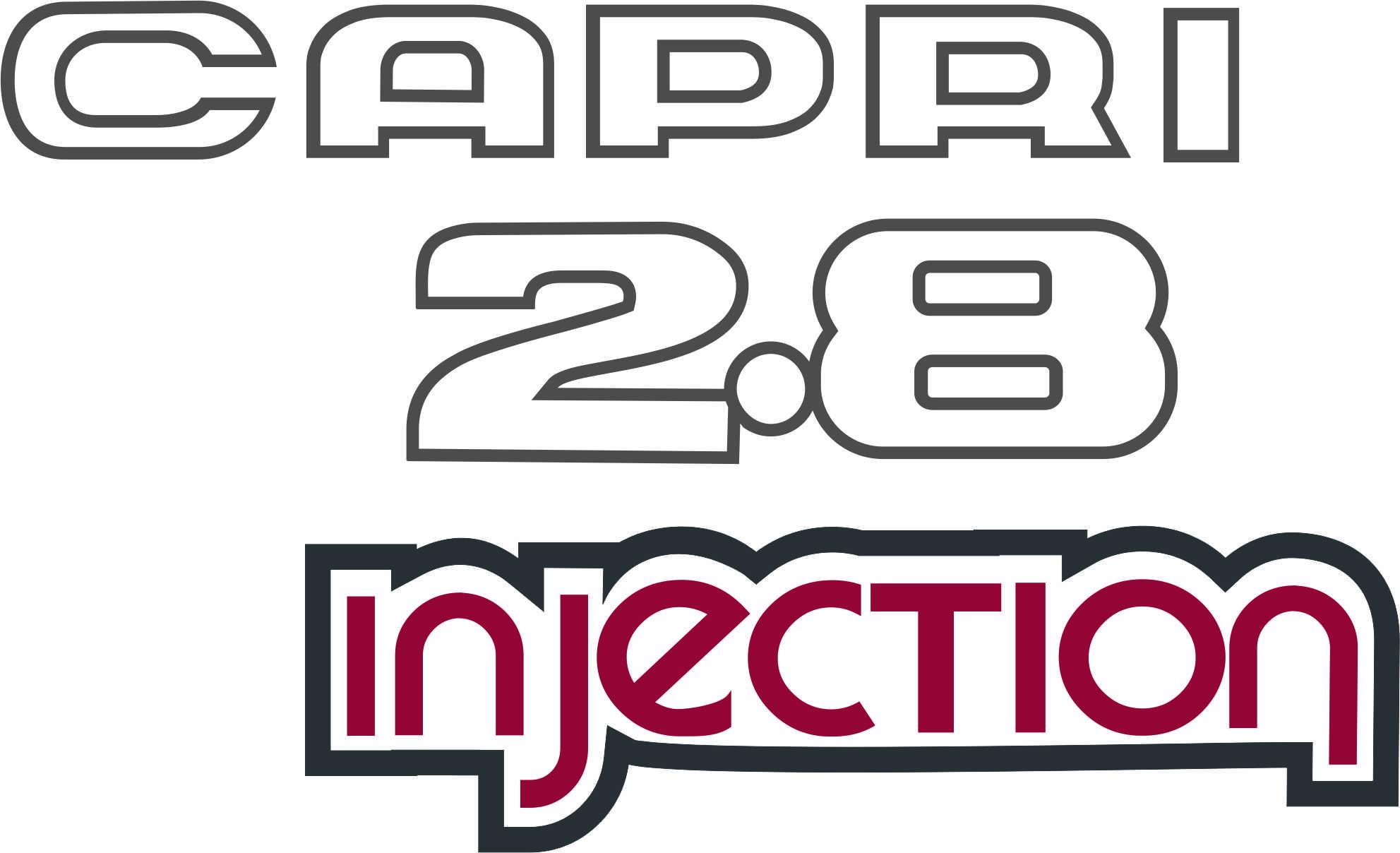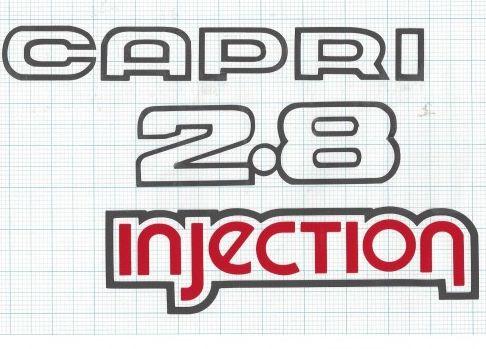
Suche die schrift von Capri 2.8
Da ich Leie bin und nichts finde, kann mir velleicht jemand hier helfen
Welche Schrift ist das von folgendem Bild ..
Solche Schriftzüge wurden üblicherweise gezeichnet, gestaltet, konstruiert oder wie auch immer, aber nicht aus einer bestehenden Satzschrift erstellt. Ich würde in diversen Ford-Foren schauen, ob das jemand schon nachgebaut und vektorisiert vorliegen hat.
Viel mehr als damit wird man dir wohl nicht helfen können :-?Vielleicht gibt es ja ähnliche, ich habe aber keine Ahnung, ob dir das helfen würde …
Aber zurück zum Schriftproblem:
Grundsätzlich gibt es digitale Schriften ja gerade erst 3 Jahrzehnte, davor gab es für Frafiker noch etwas mehr als ein Jahrzehnt Letraset-Abreibeblätter, die aber eben auch nur schwarze Schrift aufs Papier bringen konnten.
Wer davor irgend was als Schrift in sein Design bringen wollte, konnte entweder nur versuchen, beim Akzidenz-Drucker seines Vertrauens darauf zu hoffen, das der in seinem oft kleinen Schriftensortiment eine passende Schrift hat, und einem das mal eben setzt und abnudelt, sodass man dies dann abpausen kann.
Oder eben, man hat seine Schrift komplett selbst gezeichnet.
Gerade wenn es dann daran ging, einen Namensschriftzug für einen Autohersteller zu gestalten, war es aussichtslos, da nach einer fertigen Schrift zu suchen, zumal man oft ja nur wenige Schriftzeichen benötigte.
Und dann kam der Desiger nicht selten später ein riesiges Problem, weuil dann das Autowerk das nächste Modell auch mit dieser Schrift haben will, und sicxh der Desiger zuvor beim ersten Namen keine gedanken gemacht hat, wie man denn in diesen Formen auch die anderen Buchstaben umsetzen kann.  Manchmal sind einige Buchstaben in diesen mal eben für 3 Buchstaben gezeichneten Formen gänzlich unmöglich.
Auf der anderen Seite haben auch viele aktuelle Schriften ihre Wurzeln in so einem individuell gezeichnetzen Logo.
So mein erster Versuch es nach zu bauen  .. mit den zahlen bin ich noch nicht so ganz zufrieden.
Weiß jemand eine ähnliche Schrift wie auf dem original Foto?
Deine 2 finde ich übrigens besser gelungen, als die des Originals. Die Punze vom C würde ich noch einen Tick kleiner machen, hier helfen übrigens Hilfslinien, die eigentlich jedes Grafikprogamm bietet, und beim R-Beinchen würde ich noch mal schauen.